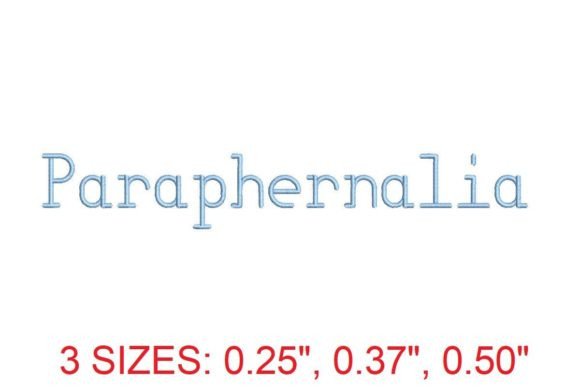
Paraphernalia Embroidery Font
«Paraphernalia Embroidery Font» — це елегантний, ручно створений скрипт-шрифт у форматі PES, спеціально розроблений для машинної вишивки з високою точністю та художньою виразністю. Він поєднує класичну каліграфічну гра ліній із сучасними технічними вимогами до вишивальних файлів: плавні з’єднання літер, оптимізовані стежки, мінімальна кількість обривів ниток і передбачувана поведінка при вишивці на різних тканинах. Цей шрифт не просто передає текст — він перетворює його на тонке художнє висловлювання, ідеальне для іменних бейджів, весільних прикрас, персоналізованих подарунків чи брендингу преміум-сегменту.
Якість збірки та технічні деталі
Шрифт надається у форматі PES (для машин Brother, Baby Lock тощо) з підтримкою розмірів від 1,5 до 5 дюймів (38–127 мм), з автоматичною адаптацією щільності стежок під розмір. Кожен символ має власну структуру стежок: заправлення без «хвостиків», збалансована кількість стоп-точок (не більше 2 на слово), а також оптимізовані кутові переходи для мінімізації «пухнатості» на тонких лініях. Включає повну латиницю, цифри, основні пунктуаційні знаки та 4 варіанти з’єднань (standard, looped, tapered, minimal). Файл поставляється з PDF-інструкцією з налаштуванням натягу ниток та рекомендаціями щодо підкладок для різних тканин.
Для кого найкраще підходить цей продукт?
Цей шрифт ідеально підійде професійним вишивальникам, дизайнерам вишивки та малим виробництвам, які цінують точність, консистентність і високий рівень фінішу. Також він стане в нагоді творчим особам, що працюють з персоналізованими продуктами (весільні аксесуари, дитячі речі, брендовані подарунки), де важлива не лише читабельність, а й естетична цілісність вишивки. Не рекомендовано для новачків без досвіду роботи з PES-файлами або для масової вишивки з жорсткими термінами — через високу деталізацію вимагає додаткової перевірки на тестових зразках.
Як це порівнюється з конкурентами
На відміну від загальновідомих скриптів, таких як «Lavender Script» або «Sweet Pea», Paraphernalia має набагато вищу оптимізацію для реальних умов вишивки: менша кількість перехресних стежок, відсутність «непередбачуваних» петель і стабільна ширина лінії навіть у малих розмірах. Порівняно з комерційними шрифтами від OESD або Amazing Designs, Paraphernalia пропонує більш унікальну, менш «шаблонну» естетику, але вимагає трохи більше уваги до налаштувань — це компроміс між автентичністю та універсальністю.